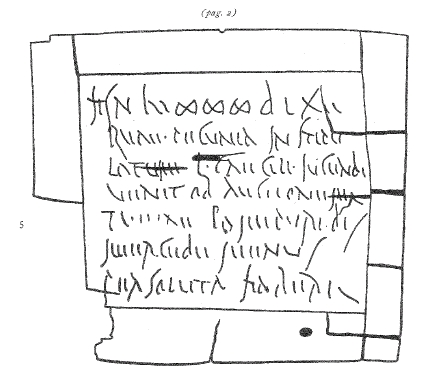
Leder prägen (Diethelm Antiqua) oder Lasern (andere Schrift)
ich würde gerne eine Leder-Laptop-tasche prägen lassen, wobei die Prägung den charme eines alten (lateinischen) Buches haben soll. Das Problem ist, das die einzig schöne Serifen-Schrift, die der Buchbinder, bei dem ich war hat, ist die Diethelm Antiqua.
Ich hätte aber eigentlich gerne eine römische Capitalis gehabt.
Jetzt stehe ich also vor der Frage, ob ich das prägen lasse mit der vorgegebenen Schrift oder es doch lasern lasse und dann die Schrift frei wählen kann.
Es geht um den Begriff FILIUSLIBRI (oder auch FiliusLibri oder Filius Libri, was meint ihr)
Hat jemand von euch die Diethelm und könnte mir diese zwei Worte mal in einer PDF schicken, damit ich sehen kann, wie’s aussieht.
Was meint ihr? Lasern oder (blind) Prägen? Und wenn Lasern welche Schrift?
PS: Falls jemand noch eine Idee hat, was man für eine passende Grafik (zu Apple/MacBook) aufbringen könnte, bin ich auch da für Vorschläge durchaus offen. Wenn ich ne Grafik finde, muss ich allerdings eh lasern lassen, weil mir ein Klischee dann doch zu teuer ist …
Ich dachte schon an das Apple-Logo irgendwie mit einer Konstruktionsanweisung versehen etwa so wie hier, aber das bekomme ich nicht hin
Muß es denn unbedingt nach einem lateinischen Buch aussehen? Geprägte Ledeeinbande hatten die Römer nicht, deshalb wäre mir das nicht authentisch genug.
Ich würde bei der Diethelm sofort zuschlagen, denn ich finde, sie ist eine wundervolle Schrift, und meines Wissens digital nicht verfügbar! Deine Tasche wäre damit was wirklich besonderes.
Die Schreibung „FiliusLibri“ würde ich auf keinen Fall verwenden. Entweder „FILIUS LIBRI“ (natürlich ordentlich spatiiniert!) oder „Filius Libri“.
Wegen eines Bildchens würde ich mal hier suchen, ob da was geeignetes dabei ist:
Das würde ich dann aber auch prägen lassen, und wenn das zu teuer würde, eher das Bild weglassen.
Wenn ich was mit einer Grafik mache, dann geht nur Laser, weil es andernfalls zu teuer würde. Allerdings weiß ich auch noch nicht, wie viel das Lasern kostet …
Also, wenn es schon antik römisch aussehen soll, dann natürlich FILIVS LIBRI… :tutor:
Aber Latein und Leder ist ja als Kombination wohl eher mittelalterlich – da wäre vielleicht eine authentische Unziale oder Minuskel passender.
ja natürlich V statt U, hatte ich vergessen … aber nur bei Großbuchstaben oder? Im Moment tendire ich eh zu Filius Libri
in was haben denn die Lateiner ihre Bücher verpackt? Oder blamiere ich mich grad, weil die noch gar keine richtigen Bücher hatten?
ja natürlich V statt U, hatte ich vergessen … aber nur bei Großbuchstaben oder?
Kleinbuchstaben kamen ja erst im Mittelalter auf. Also »FILIVS« authentisch oder »Filius«, dann aber unrömisch.
in was haben denn die Lateiner ihre Bücher verpackt? Oder blamiere ich mich grad, weil die noch gar keine richtigen Bücher hatten?
Buchrollen gab es, auf sehr teurem Pergament oder nicht ganz so teurem Papyrus. Papier war noch nicht.
Du könntest natürlich auch die echte römische Handschrift nehmen – allerdings dürfte das dann kaum jemand lesen können… ;-)
Auf dem Bild steht:
„sii n iↄↄmmmdlxii
quae pecunia in stipu-
latum l caecili iucundi
venit ob auctionem
tulliae lampuridis
mercede minus
persoluta habere“
Die hatten neben Rollen noch sowas.
Aber das Laptop in eine Holzkiste packen? :neenee:
Nein, das Kalb bzw. dessen Haut hab ich schon gekauft und daraus wird die Tasche auch gemacht. Also: Weniger authentisch bzw. eher mittelalterlich alt.
Die handschrift kann ich ja nicht schreiben, würde aber behaupten, das mein Freund – für den die Tasche ist – bestimmt lesen könnte.
Ich werde mich dann wohl für „Filius Libri“ auf dem „Buchrücken“ entscheiden. Vielleicht zusätzlich noch ein doppeltes Aldusblatt (das ist die einzige Form, die die Buchdruckerin hat).